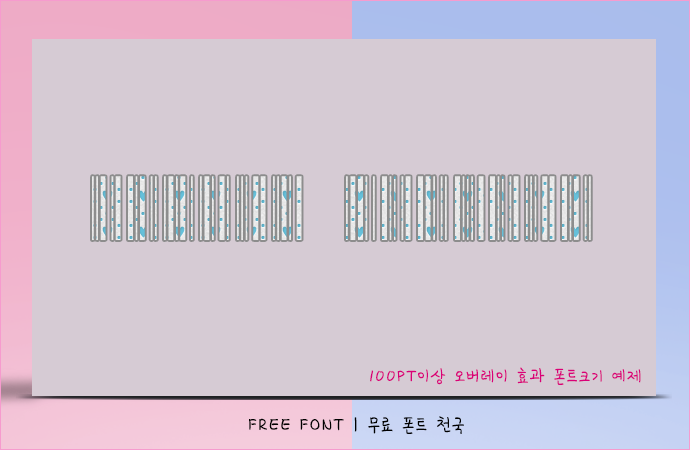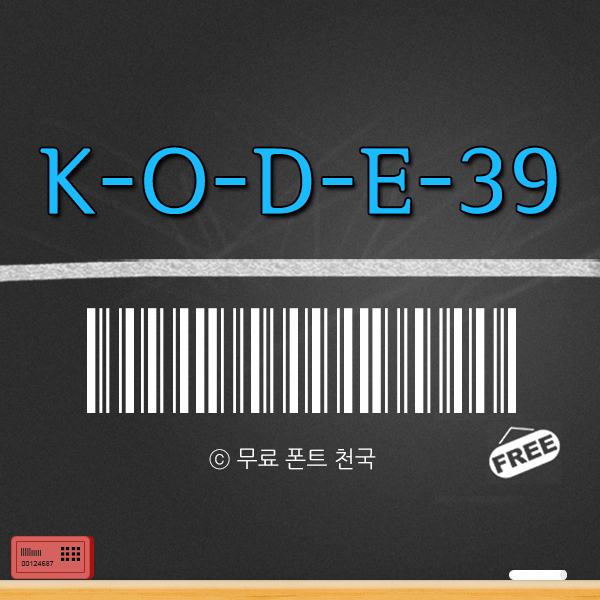
정밀한 스타일 KODE39 바코드 폰트
촘촘하게 제작된 KODE39 바코드 서체입니다. 누구나 자유롭게 사용 가능합니다.
KODE39 , 12~80PT 크기로 가독성을 테스트 해본 폰트
KODE39 , 100PT 크기 이상으로 작업한 오버레이 효과를 적용한 폰트
KODE39 , 100PT 크기 이상으로 그레이언트를 효과를 적용한 폰트